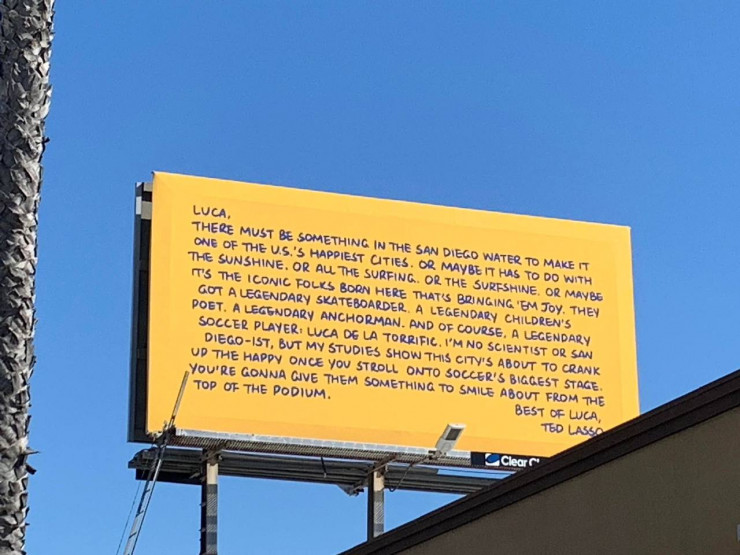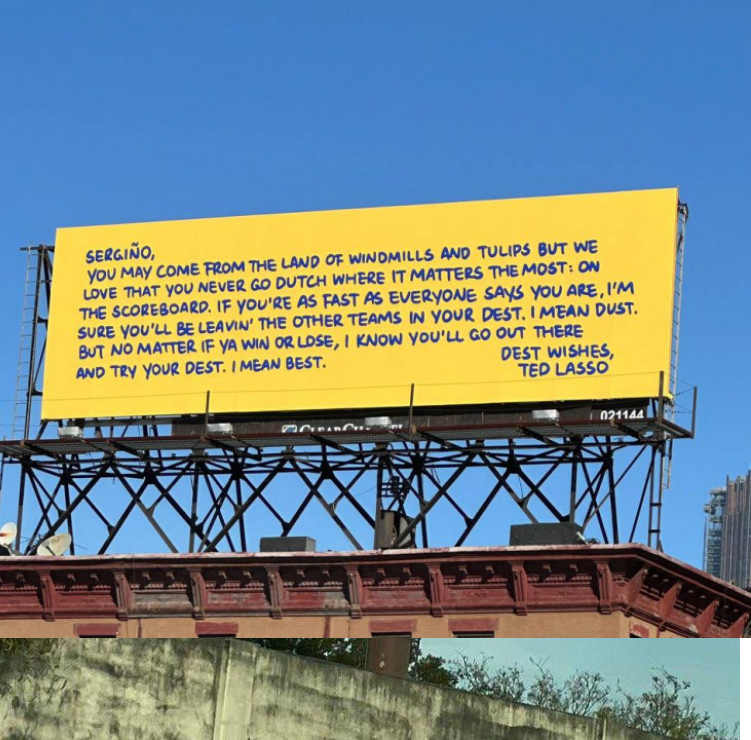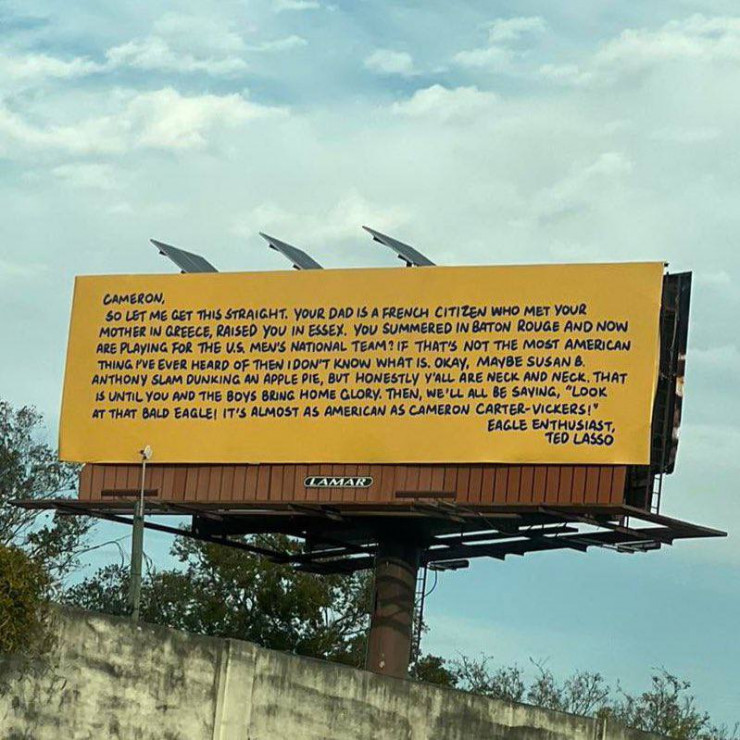
Можно ли в наружке использовать только мелкий шрифт без картинки
Да, если точно знаете, что добъетесь WOW-эффекта.
Сериал «Тед Лассо» о тренере по американскому футболу, который внезапно возглавил английский футбольный клуб «Ричмонд», лично нам не зашел — посмотрели несколько серий и бросили.
А вот в США он настолько популярен, что его главного героя использовали в качестве мотиватора американской сборной перед ЧМ-2022. В важных для игроков городах и штатах разместили билборды с письмами Лассо игрокам команды. В их текстах много локальных отсылок и непереводимой игры слов.
Послание к члену американской сборной из «Милана» Серджиньо Деста, например, начинается так: «Серджиньо, ты появился на свет на родине ветряных мельниц и тюльпанов, но нам нравится, что ты никогда не появишься на табло с голландской стороны…»
А Кэмерон Картер-Викерс из «Селтика» удостоился самого забавного письма: «Кэмерон, давай поговорим начистоту. Твой папа — гражданин Франции, который встретил твою маму в Греции, а потом вырастил тебя в Эссексе. Потом ты приехал в Батон-Руж, а сейчас играешь за сборную США. Если это не самая американская вещь, которую я когда-либо слышал, то не знаю, что это тогда».